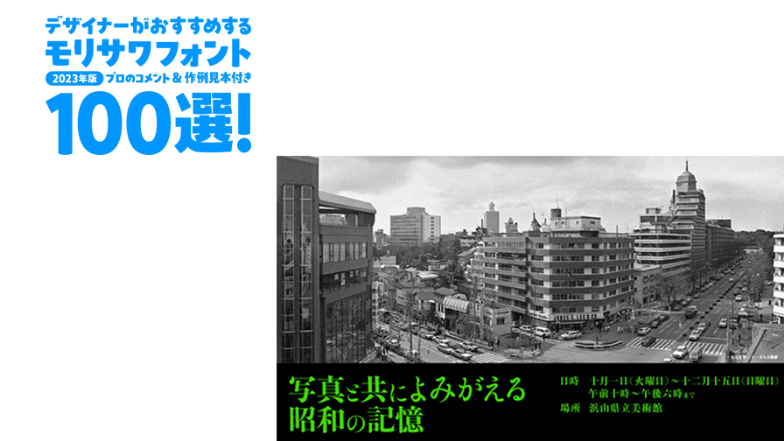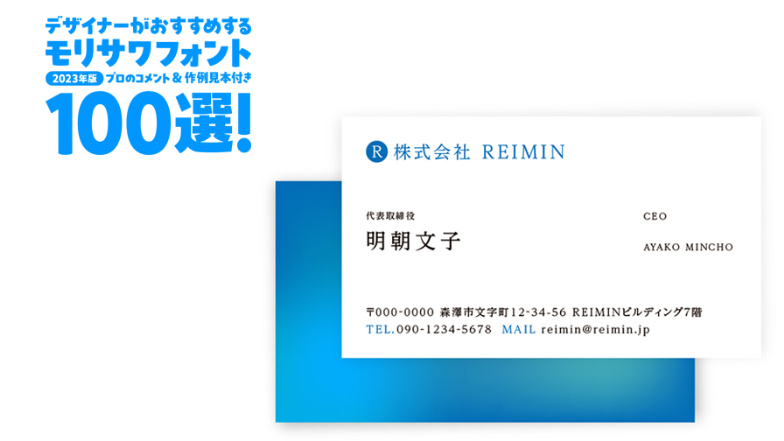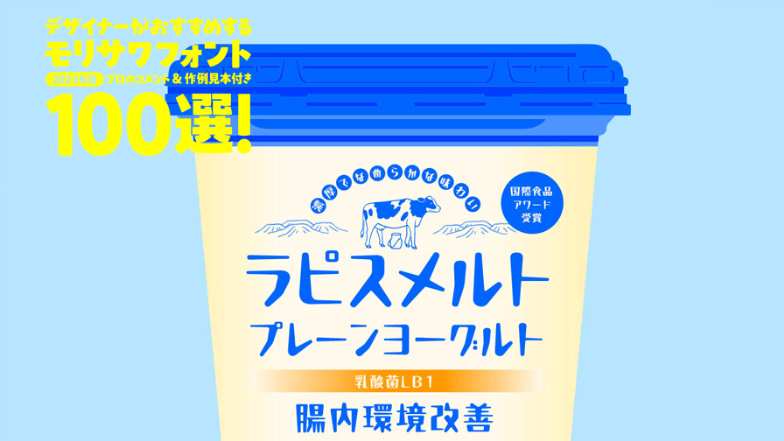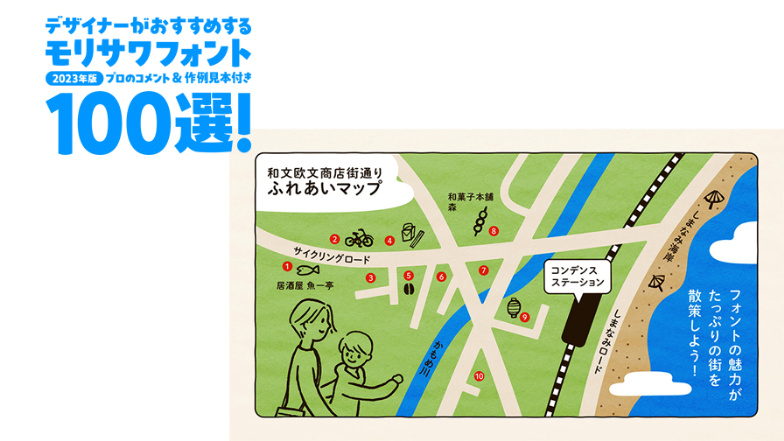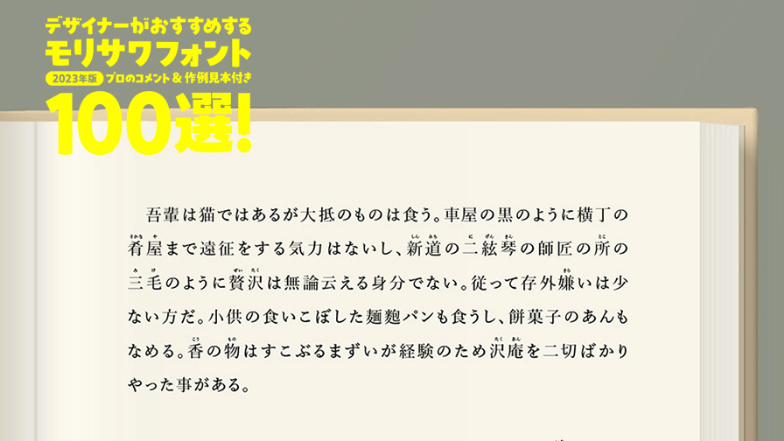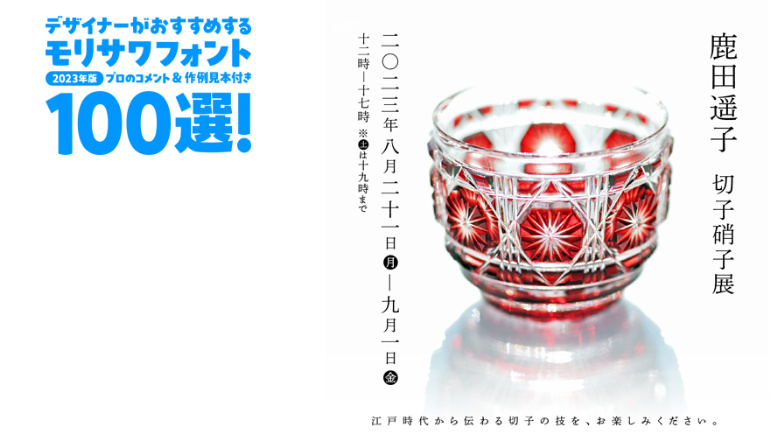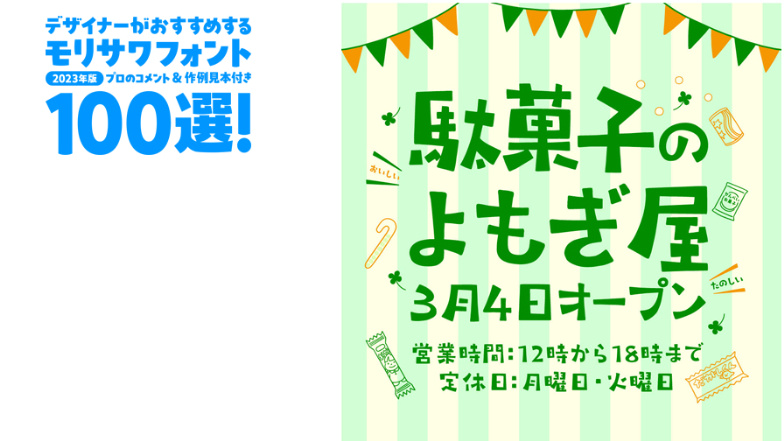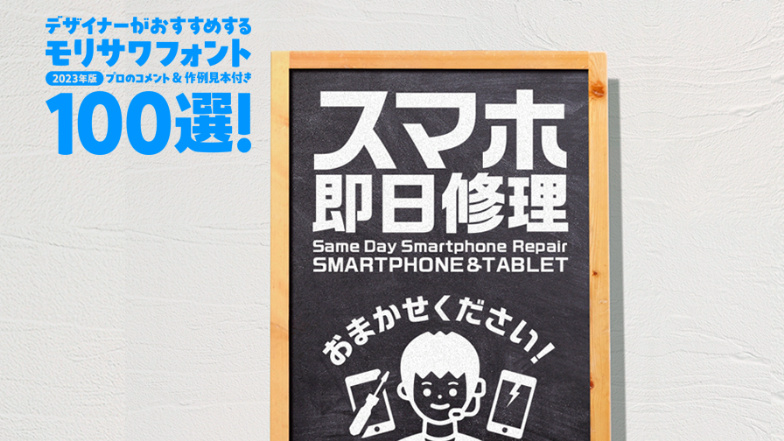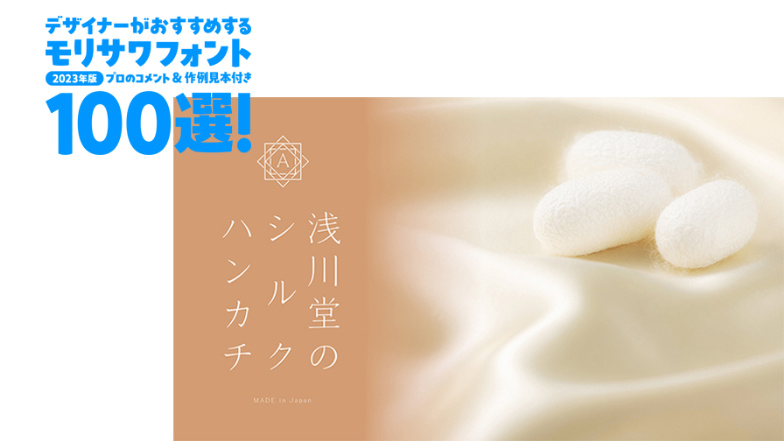
デザイナーがおすすめするモリサワフォント100選!「定番」「楽しい」「力強い」etc... といったキーワードから用途別に調べられるフォントの逆引き辞典。書体の特徴を活かした作例の見本付きで、書体の特長やポイントを丁寧な解説します。記事は随時更新。
プロ御用達のド定番! 端正な印象のフォントでキリッと見せるのに最適な明朝体「リュウミン」
時代小説の本文のフォントは何が最適? クラシカルな印象で上品に見える「游明朝体」がベスト
見やすいフォントで現代的な印象に仕上げるには? 汎用性も高い「新ゴ」の活用がオススメ
肉声を感じさせたい見出しには「ゴシックMB101」が便利。信頼感のある王道フォントを使うべし
【裏ワザ?】キャプションの定番「中ゴシックBBB」をアケ組の見出しに使ってみる活用例
オーソドックスに見やすく仕上げるには? 活字書体のデザインを忠実に引き継ぐ「太ゴB101」
スッキリと1文字ずつ見やすい文字列を組むなら、小さめの字面でベーシックな「游ゴシック体」
フォーマルな宛名書などに最適なフォントとは? オーソドックスな楷書体の「正楷書CB1」
教科書や参考書などのデザインで選ぶべきフォントは? 教育分野に必携と言える「教科書ICA」
印章などで使われる隷書で高級感のある看板などに! 歴史とともに新鮮さも感じさせる「隷書E1」
きちんとした雰囲気とおしゃれさを両立させるなら? 明朝体とゴシック体の中間的な「UDタイポス」
活字のような雰囲気の見出しを作るには? 滲み加工でアナログ感もある「秀英にじみ四号太かな」
王道の明朝体で文字列を読みやすく組む! かな文字の筆の勢いも魅力的な「本明朝新がな」
スマホで表示される本文を読みやすく! ニュートラルで字面が小さい「あおとゴシック」
清潔感を伝えたい美容商品のパッケージなどに最適! 文字が縦長で左右の余白が広い「エコー」
どことなくレトロな雰囲気が漂う縦長の「オーブ」で、占いや風水を連想させるフライヤーを表現
本文にも組みやすいシャープなフォントを使いたいときは、名刺や案内状にも役立つ「花胡蝶」がおすすめ
誤読されにくい名刺を1つのフォントで作るには? 英数字もシンプルで見やすい「UD黎ミン」
ユニバーサルデザインに配慮した案内板を作るなら? 英数字も見やすい「UD新ゴ」
看板の文字を優しい雰囲気に仕上げたい... 可読性も高く親しみやすい「UD新丸ゴ」がおすすめ
細長い商品パッケージで便利なフォント。多くの文字を掲載できる「UD新ゴ コンデンス70」
パッケージや動画テロップなどで、独自の世界観を表現したいときにオススメな「ラピスエッジ」
装飾性の高いフォントで独特な雰囲気を表現したい... ブラックレター風のデザインの「オズ」がおすすめ
レトロモダンな雰囲気に立体感をプラスするには? 西洋風のストロークで装飾性が高い「白のアリス」
きらびやかな印象やロマンチックな雰囲気を演出するには? カールが可愛い「翠流デコロマン」
長い歴史に裏打ちされた安定の読みやすさ! 本文組みが落ち着いた雰囲気になる「秀英明朝」
電子書籍コンテンツの縦組みの本文に適した明朝体はこれ! 画面上で読みやすい「凸版文久明朝」
日本文学の本文を美しく組むには? 情緒を感じさせる表現との相性が抜群の「文游明朝体」
ゴシック体でありながらも温かみや優しさを感じる、墨だまりと角丸加工が特徴的な「A1ゴシック」
文字の余白まで美しい! 挨拶状などで情感溢れる風情や品格を表すことができる「欧体楷書」
平体にして本文を組んだ「毎日新聞明朝」で、あっという間に新聞や広報誌のイメージを再現する
新聞らしさがひと目で伝わる! 新聞の見出し用に設計されている「毎日新聞ゴシック」
新時代にふさわしい教科書体! タブレットで表示させる教材などにおすすめしたい「UDデジタル教科書体」
文芸を彷彿とさせるクラシカルな雰囲気の「霞青藍」楷書の要素も強いオールドスタイルの明朝体
オールドスタイルでありながらも洗練された雰囲気の「霞白藤」でエレガントに見せる!
格調高くて洗練された媒体の見出しに最適なフォントは? 田中一光氏の文字がもとになった「光朝」
吹き出しのセリフを漫画らしく表現するならこれ! アンチゴチの発想に基づく「秀英アンチック+」
強いインパクトと親しみを両立させるには? 大きな文字で使いやすい「ハルクラフト」
“和” のパッケージでこだわりを見せたい! 豪快な見出し用フォント「黒曜」で大胆に演出
和風のデザインで躍動感を出したいなら? カッコ良く仕上がる筆書系の「剣閃」が便利
インパクトのある現代的なロゴを作るには? デジタル表現にマッチしやすい「G2サンセリフ」が◎
正統派の堅い印象とインパクトを両立するには? 極太でどっしりした「楷書MCBK1」がおすすめ
日本らしいイベントや催しの告知に最適なフォントは? 骨太で威勢の良い「勘亭流」の採用
質の良さや高級感を醸し出せる人気フォント「A1明朝」で柔らかな温かみを演出する!
フォーマルな場面で情緒を表現するには? 明朝体に毛筆のエッセンスを加えた「しまなみ」がオススメ
格調高い雰囲気のあるフォントでのレトロ表現! 漢字が龍の爪のような鋭いイメージの「かもめ龍爪」
伝統的なフォントで展覧会のタイトルを映えさせる! 金属活字に由来する「游築見出し明朝体」
滲みのあるフォントでレーザー加工を再現! 伝統ある「秀英にじみ角ゴシック金」の多彩な活用テクニック
インク溜まりの再現で温かみを演出! ポスターなどでインパクトも出せる「欅角ゴシック Oldstyle」
品のある穏やかな雰囲気を感じさせる「花牡丹」で味わい深いレトロなイメージを表現
レトロポップであどけない雰囲気の「ココン」を使って、初めての人でも手に取れる手芸本を作る
オーガニックや無添加などの商品パッケージには、柔らかな「白妙 オールド」で優しさを強調
クラフト感のある独特な個性を放ち、ノスタルジックな雰囲気と素朴な魅力を備える「くれたけ銘石」
ほのぼのした雰囲気の丸ゴシック体で、優しい印象と落ち着きのあるデザインの「秀英丸ゴシック」
明朝体とは少しだけ違った雰囲気に仕上げる手法。自由なエレメントで温かみのある「モアリア」
アットホームな楽しさを演出するには? 躍動感があって丸や三角のエレメントが可愛い「タカリズム」
画線の交差部分の黒みが特徴の「タカモダン」で懐かしさのあるレトロモダンな楽しさを表現
優しい味わいと親しみやすさを演出。気心の知れた優しい手書きの印象が強い「那欽」
カジュアルな内容に筆文字系のデザインフォントを使うには? ポップな雰囲気の「プリティー桃」がおすすめ
力の抜けたような適度な “ゆるさ” が魅力! 文字の中に大胆な余白がある「はるひ学園」の活かし方
縦組みの文字で手書きならではの温もりを感じさせる あえて整い過ぎない書風の「うたよみ」の活用法
ゆったりとした優しいイメージを伝えるには? レトロで素朴な印象のかな文字「小琴 京かな」の活用例
フェルトペンで手書きしたような運筆を表現したい! 自然な雰囲気で親しみを感じる「ぺんぱる」が最適
ほっとひと息つけるような柔らかさを表現するには? 親しみやすい「ぽっくる」がオススメ
素朴で可愛らしく伸びやかに見せたい!「タカ風太」で演出できる自由な手作り感のイメージ
ゆる可愛い雰囲気でデザインできるフォントはこれ! あどけない可愛さのある脱力系の「ぽってり」
親しみやすさと読みやすさを両立! 子ども向けの絵本などにも最適な丸ゴシック体の「じゅん」
子ども向けのアイテムを楽しく演出! かな文字が可愛いコロコロとキュートな「つぶてん」
洗練された大人の可愛さを表現できるフォントは? 縦長のプロポーションが魅力の「翠流きら星」
正確な内容を真面目に伝えつつもキュートさをプラスできる! 親近感を与える「丸フォーク」
語り言葉をはじめ動画の字幕や絵本など、やわらかい言葉を組む際に効果を発揮する「トーキング」
文字を並べるだけでも手軽にロゴのような雰囲気を実現! 親しみやすさのある「すずむし」
1980年代を想起させる可愛いイメージの表現にぴったり! 斜めに傾いた勢いのある「くろまめ」
古風でレトロな可愛らしさを表現できるフォントは? 平体ぎみのプロポーションが印象的な「ちさき」
書体でおしゃれな可愛さを強調! 有機的なたわみを持つ明朝体風のデザインフォント「プフ ソワレ」
打ち出したい際にも最適! すっきり見せながら可愛らしさとインパクトを出す「翠流ネオロマン」
楽しい
リズミカルな雰囲気を書体で表現するなら? 手書きの温かみも同時に演出できる「はせミン」
映画のような雰囲気をフォントで演出するには? 字幕の文字から作られた「シネマレター」
フォントのアクセントでリズム感を表現するには? ドットのエレメントが楽しい「タカハンド」
無骨さと親しみやすさを両立させながらインパクトを出すには? 角張った独特な造形の「竹」
子ども向けのシーンにぴったり、立体的な文字で楽しさもUP! 食い込みがユニークな「トンネル」
文字中心のデザインでも動きのある勢いを演出! 蜘蛛の糸を想起させる線が斬新な「くもやじ」
和モダンのデザインで、続け字の手書きのイメージを表現するなら? 連綿体を利用できる「みちくさ」
おどろおどろしい雰囲気を演出したいときには? 切欠部でのかすれが特徴的な「TB古印体」
溶けるようなイメージを強調するには? 直線的でありながらもやわらかな「ラピスメルト」
ナチュラルでポップな食品のイメージにぴったり!ペンでさりげなく書いたような「プフ ホリデー」
元気さと同時に肩の力が抜けた可愛さを表現(演出)特徴的なカーブを持つ「プフ ポッケ」
パッケージや動画テロップなどを明るく見せるには? はつらつとした印象の「プフ ピクニック」